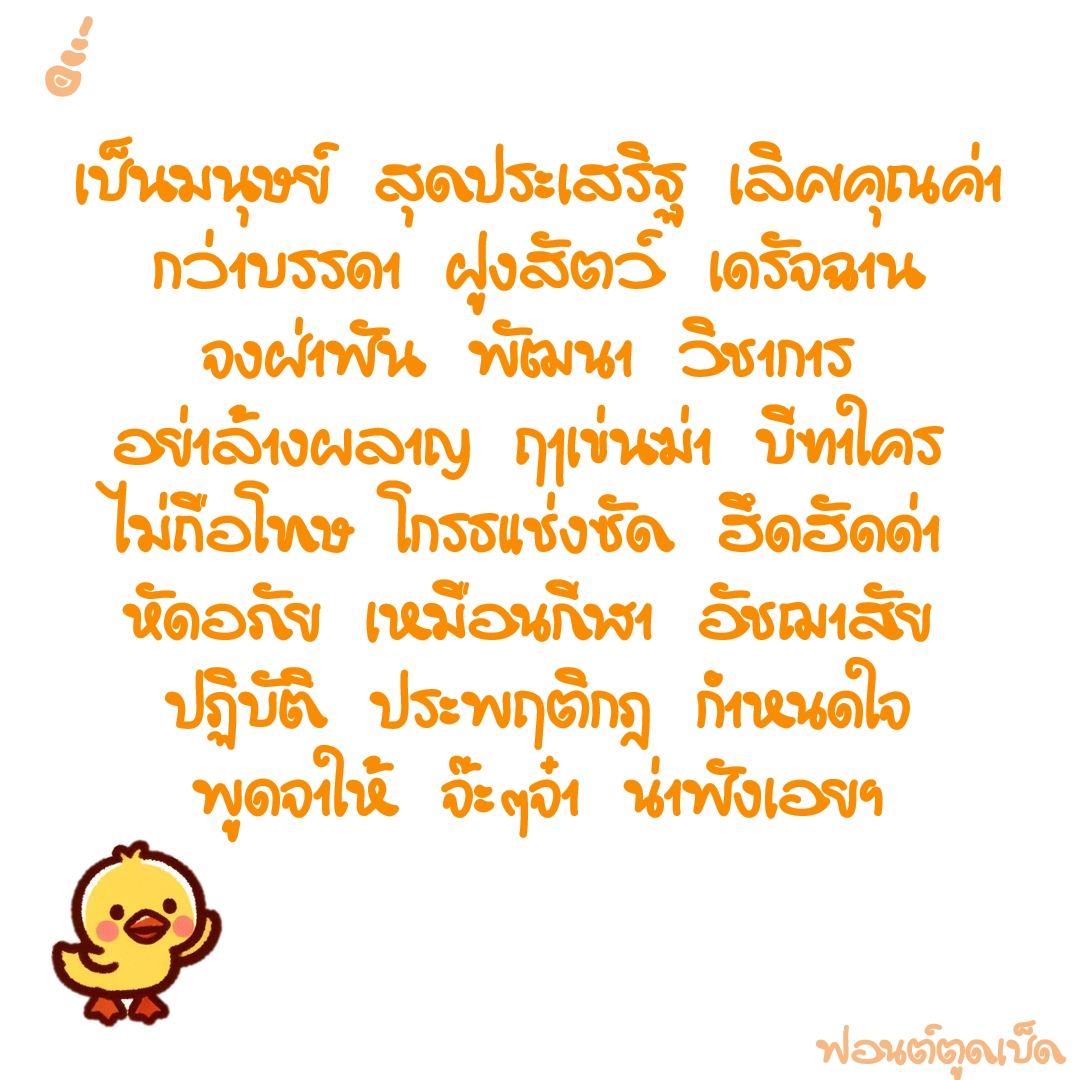
ฟอนต์ ตูดเป็ด
อยากทำอักษรตวัดปลายหางให้งอนขึ้น เหมือนตูดเป็ด ..ทำให้เกิดช่องไฟที่กว้างมากไป ต้องตามแก้ปัญหาให้วุ่นวาย
ตั้งใจให้เป็นฟอนต์พาดหัว แต่ดูเหมือนเป็นข้อความก็พอได้ ..เชิญนำไปสะบัดตูดตามสบาย เงื่อนไขเขียนไว้ชัดเจน
ชื่อฟอนต์ : ตูดเป็ด
อยากทำอักษรตวัดปลายหางให้งอนขึ้น เหมือนตูดเป็ด ..ทำให้เกิดช่องไฟที่กว้างมากไป ต้องตามแก้ปัญหาให้วุ่นวาย
ตั้งใจให้เป็นฟอนต์พาดหัว แต่ดูเหมือนเป็นข้อความก็พอได้ ..เชิญนำไปสะบัดตูดตามสบาย เงื่อนไขเขียนไว้ชัดเจน